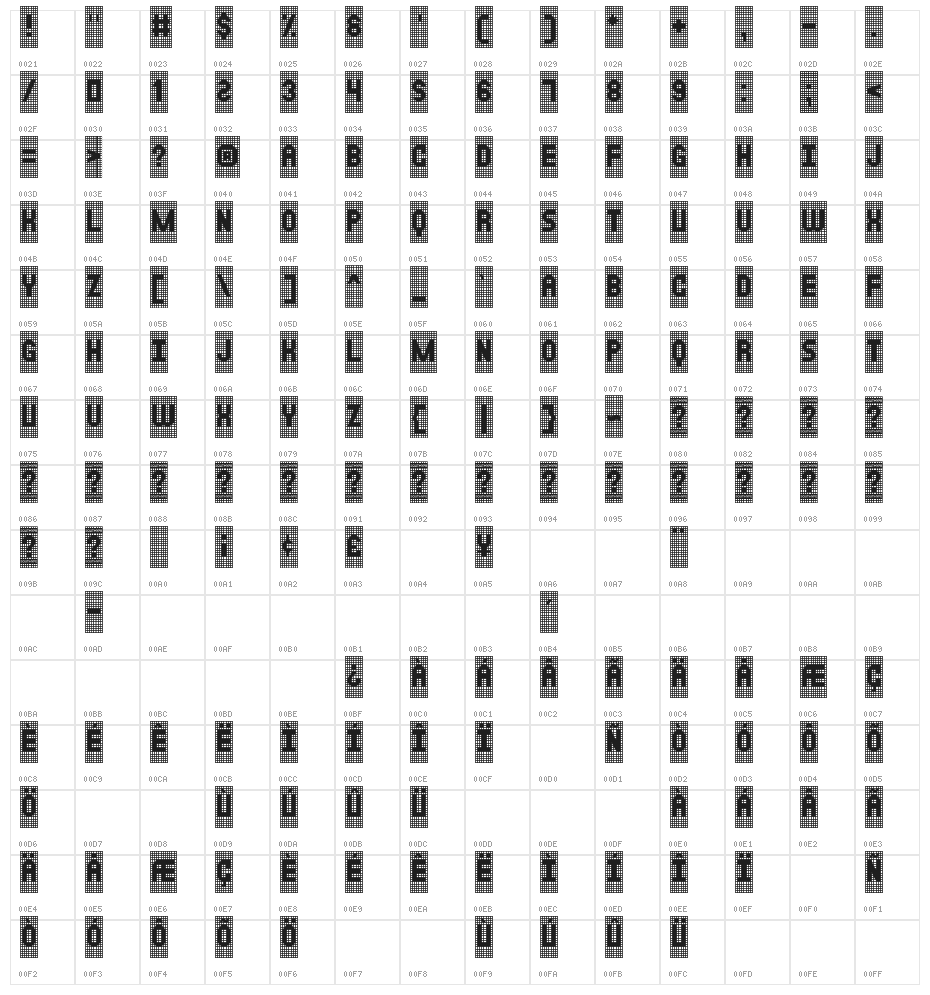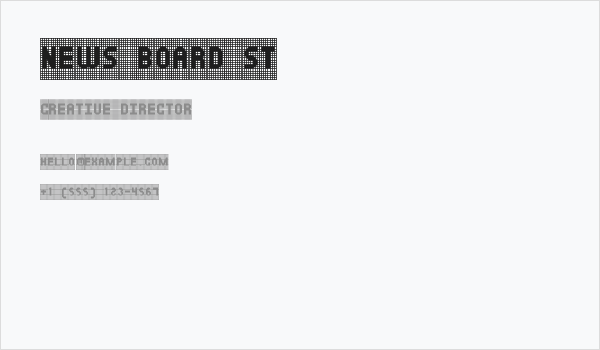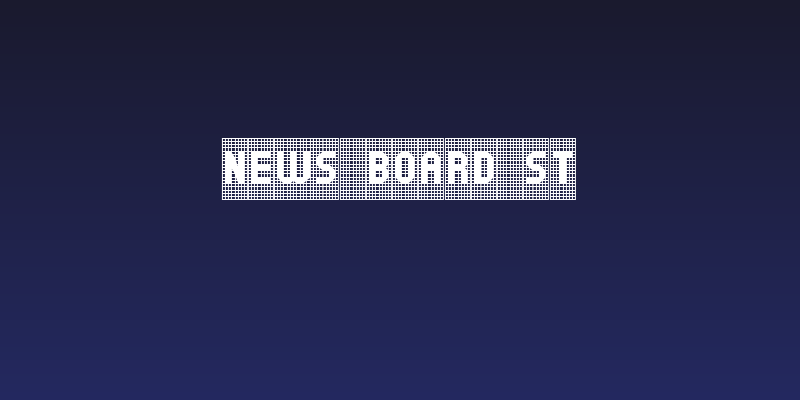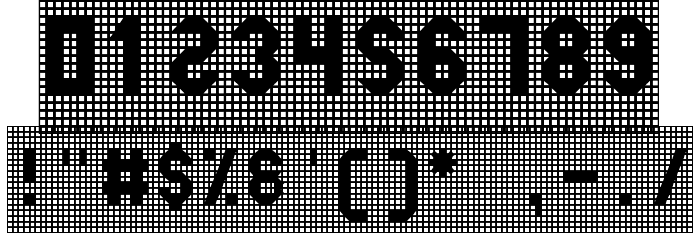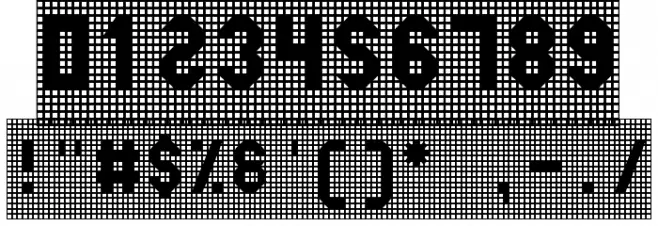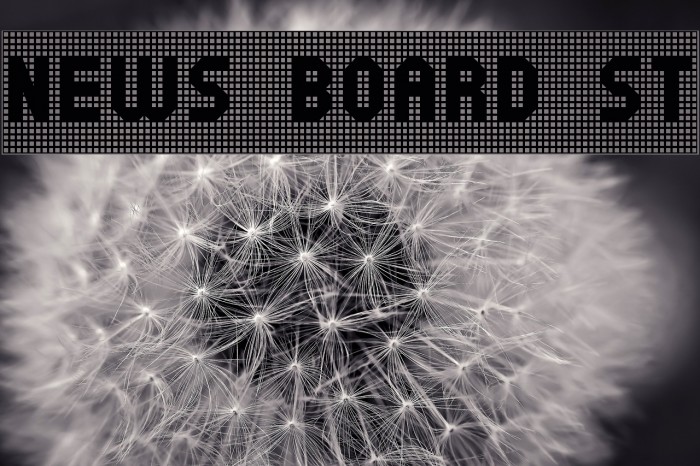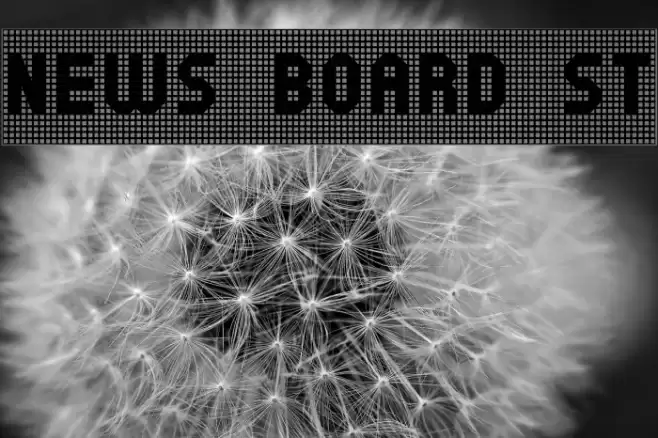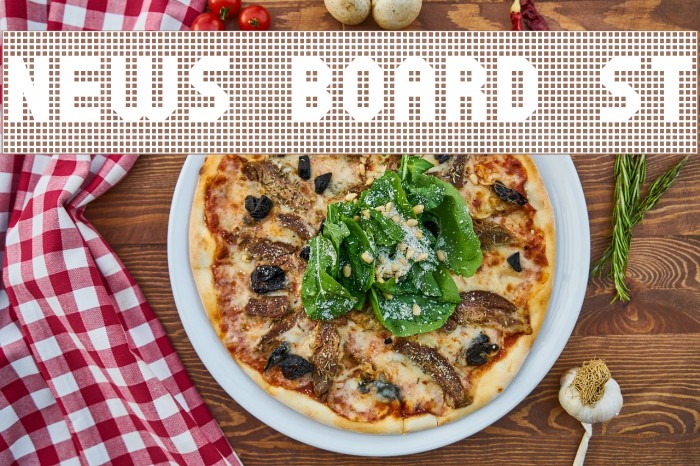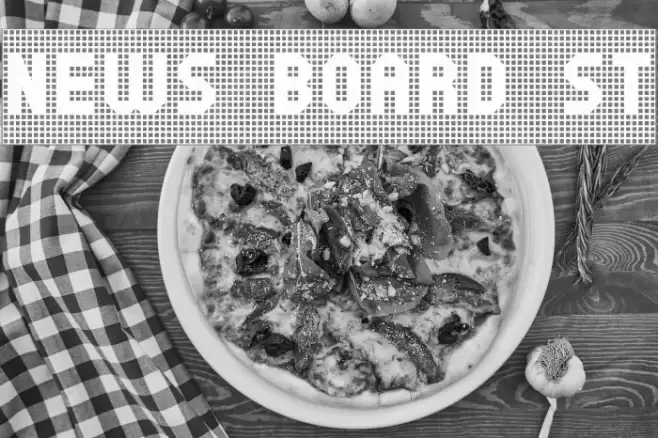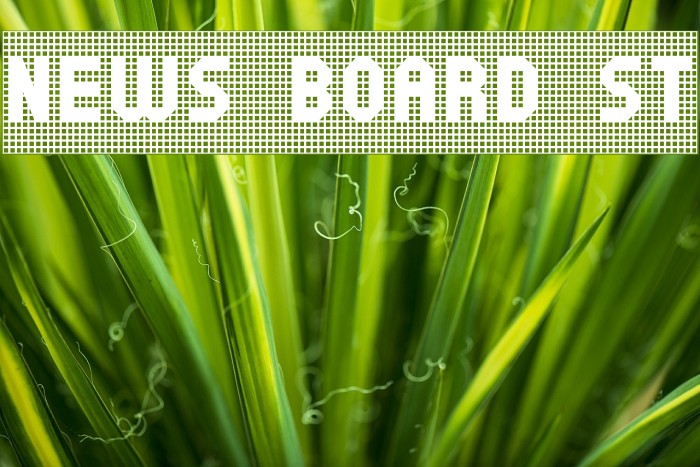
News Board St Font
✎ Pixel
| Stil general | Retro, Digital |
| Caz de utilizare | Headlines, Logos, Digital displays |
| Proiecte propuse | Ideal for digital displays, retro-themed designs, tech branding, and video game graphics. |